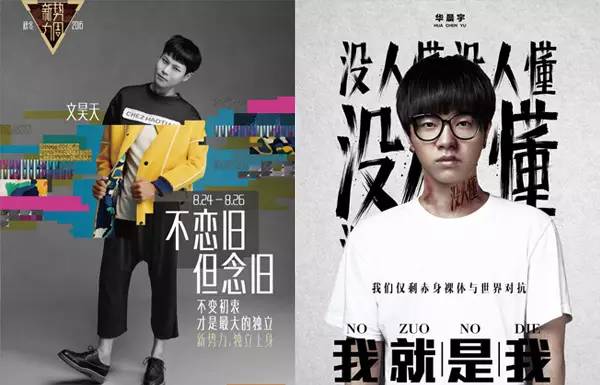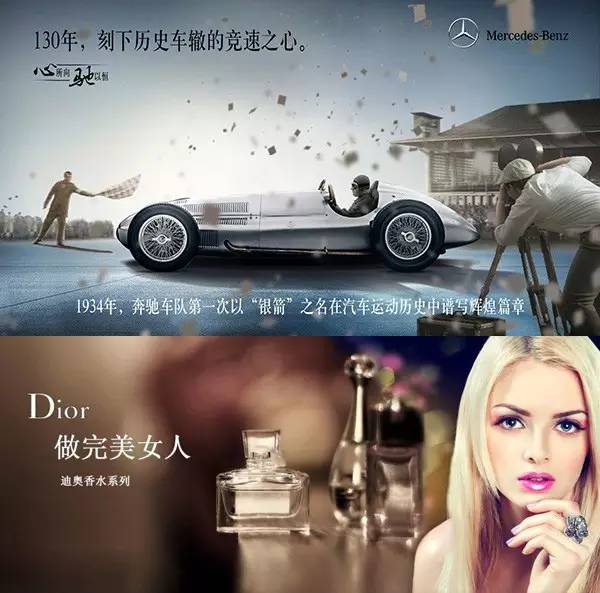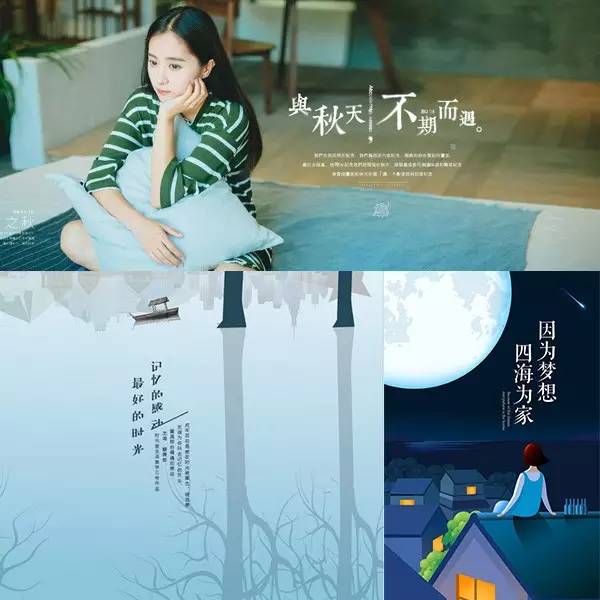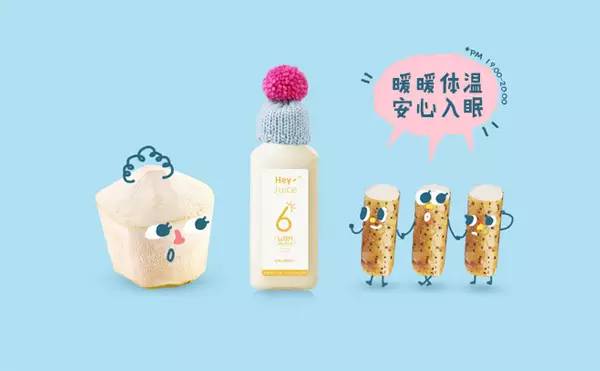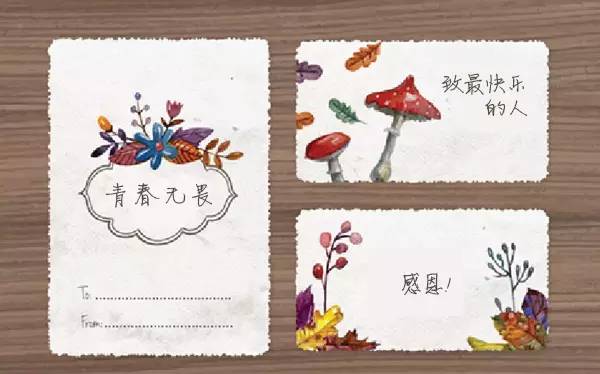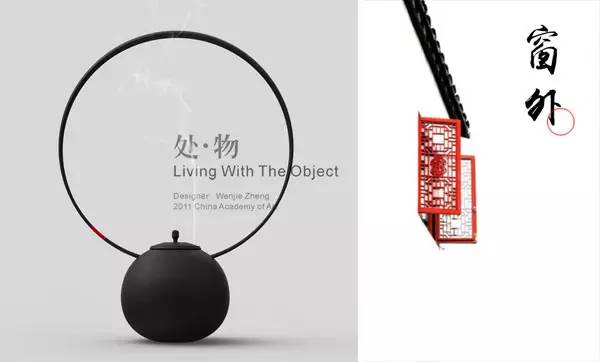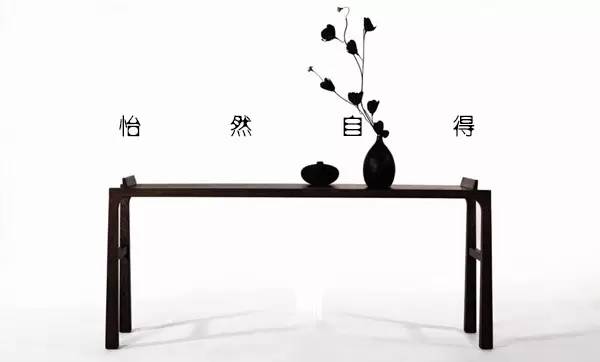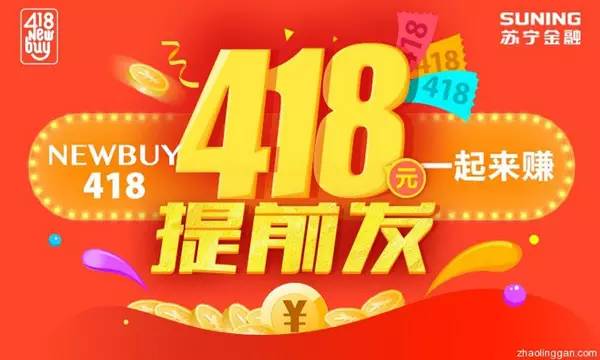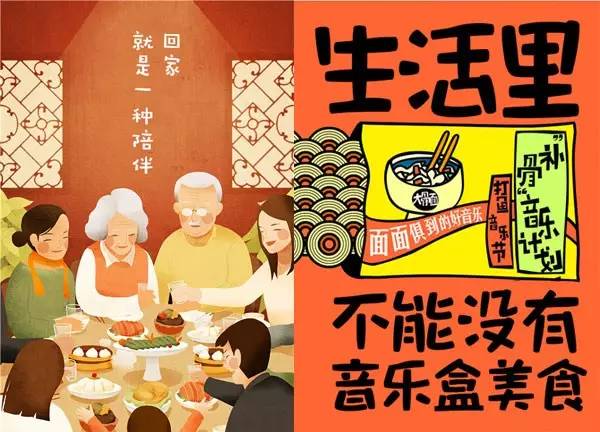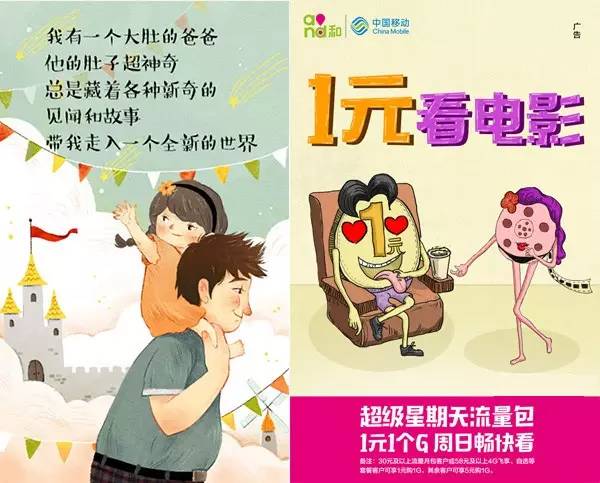
适配 8 大常见设计风格的 43 款字体汇总
每一种字体都能传达独特的视觉感受,适用于不同风格的设计,所以每个设计师的电脑里都会装有数百种字体以供选择,然而,真到设计的时候,很多人却挑不出一个合适的字体,那么该如何在正确的时候选择正确的字体呢?什么时候该用宋体?什么时候该用黑体?针对高大上、接地气、小清新的设计分别要用什么字体?显然这些不仅仅是处女座要面对的难题,如果你也有被这些问题所困恼,那么请接着往下读。
为了帮大家解决上面那些难题,我吐血整理了43种字体,以适应8大最常见设计风格,现在,我们一起来看看具体的使用方法。
1、高大上风
高大上风格的设计一般都比较简洁,画面元素的质感很好、背景比较干净,所以不宜使用太复杂、太随性的字体。宋体和比较细的等线体是比较不错的选择,例如:汉仪长宋、汉仪中宋、华文宋体、方正大标宋、方正书宋、方正兰亭纤黑和超细黑等,而且最好不要给字体增加过多的效果。
奔驰广告用的是拉长版的汉仪中宋,迪奥广告用的是方正书宋。
iPhone7广告用的是方正兰亭纤黑
2、年轻时尚风
针对90后所做的设计,比如葱爷这种,关键词是:时尚、个性、年轻、叛逆等,设计风格普遍都是色彩艳丽、表现形式新颖、动感较强。所以应该选择比较有设计感、有张力的字体,太规矩的字体会显得有点呆板,例如:站酷高端黑、造字工房尚黑、造字工房力黑、造字工房形黑、造字工房版黑、锐字巅峰粗黑、逼哥青春简体等,都是比较好的选择。
上面这张人人网的广告图用的是造字工房版黑,并且做了拉长和粉笔效果的处理
左上图是淘宝旗下时尚品牌新势力周的广告,用的是造字工房形黑粗体,右上图是电影《我就是我》的海报,用的是笔刷拼成的书法字体和造字工房力黑。
3、可爱风
可爱风设计主要针对人群是儿童和年轻女性,颜色饱和度比较高,画面活泼、温和有趣,所以选择的字体也应该符合这几个特点,像比较硬朗和规矩的造字工房字体和宋体在这里就不合适了,我们应该选用比较圆滑、亲和力较强的手写体和卡通字体,例如方正少儿体、汉仪粗圆简体、站酷快乐简体、华康少女文字、汉仪娃娃篆体、汉仪荔枝体、华康娃娃体、迷你胖头鱼体等等。
汉仪荔枝简体
胖头鱼简体
汉仪娃娃篆体
4、文艺清新风
文艺清新风设计是年轻女性很喜欢的一种风格,例如一些护肤品、服装广告、h5的设计就很喜欢使用这种风格,为了统一协调,我们选择的字体当然也要清新脱俗,硬笔书法字体、细长的宋体、等线体都具有这一特色,如:钟齐安景臣硬笔行书、凌惠体、方正静蕾简体、汉仪家书简体、华文宋体、方正幼线简体等。
上面的设计用的都是宋体
方正静蕾简体
5、男士风
针对男性消费者的设计自然与女性的不会一样,男性设计更倾向阳刚、大气、简单、冷酷,颜色上冷色调偏多,所以我们要选择简洁有力的字体,如:造字工房力黑、方正兰亭特黑、大黑、腾祥潮黑、锐字锐线怒放黑体、蒙纳超纲黑体、沙孟海书法字体等。
上面这折耐克广告的字体是蒙纳超纲黑体
左上飞利浦广告的字体应该是稍作了调整的腾祥潮黑,右上的健身广告应该是方正兰亭特黑。
6、中国风
中国风是客户很喜欢的设计风格,特别是在跟茶叶、保健品、土特产、瓷器相关的设计中比较多见,中国风的设计当然要配色中国风的字体,像宋体、楷体、隶书、毛笔字、都是具有中国风特色的字体,具体可以选用:华康俪金黑、造字工房刻送、方正楷体、方正华隶简体、汉仪字典宋体、方正珊瑚简体、禹卫书法行书简体等,书法字体比较少很好的现成字体,最好是叫专人手写或者用笔刷拼凑。
方正细珊瑚体
左上为宋体,又上是禹卫书法行书简体。
7、手绘风
手绘风格的设计一般具有自然、好玩、开放等特性,画面中的文字要很好的融入画面,不要抢了画面的风头,所以我们选择字体时也要以手写字体为主。例如:汉仪小麦简体、汉仪跳跳简体、方正喵呜体、方正稚艺简体、造字工房童心体、文鼎奈谷米POP体等,如果你字写的不错,也可以自己动手写。
左上为汉仪小麦简体,右上是造字工房童心体。
左上汉仪跳跳简体,右上是文鼎奈谷米POP体。
8、促销风
对于促销海报、促销单张、促销折页这类促销设计,主要目的是吸引消费者的注意、突出优惠信息等,所以要选择笔画粗且清晰有力的字体,例如方正兰亭特黑、方正正大黑、庞门正道标题体、方正汉真广标简体、雅坊美工14、造字工房力黑、造字工房典黑等等。
造字工房力黑
方正兰亭特黑
庞门正道标题体